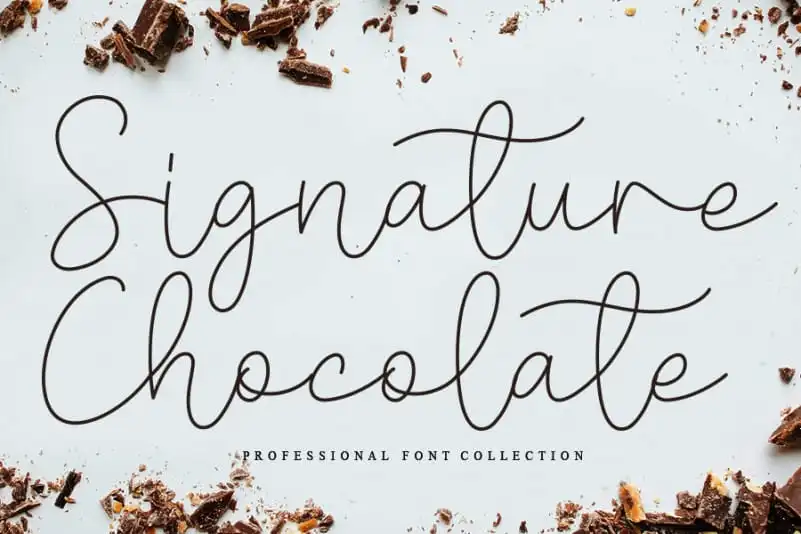
Signature Chocolate Script Font – Fonte Grátis
Signature Chocolate Script Font
Signature Chocolate Script Font é uma fonte à mão livre que transmite a essência delicada e sofisticada dos chocolates. Suas letras expressivas e elegantes evocam imagens de doces brilhando sob luz de velório, embalados em papéis luxuosos com detalhes decorativos. Esta fonte é perfeita para aqueles que buscam uma graça sutil nas suas criações digitais, seja um branding minimalista ou a capa de um livro de receitas. Ela é ideal tanto para personalizar seus trabalhos como para torná-los ainda mais autênticos e envolventes, inspirando experiências memoráveis no design. Com uma abordagem delicada, o Designer creativeletter criou uma fonte que não apenas ilumina seu trabalho, mas também transmite um encanto especial.